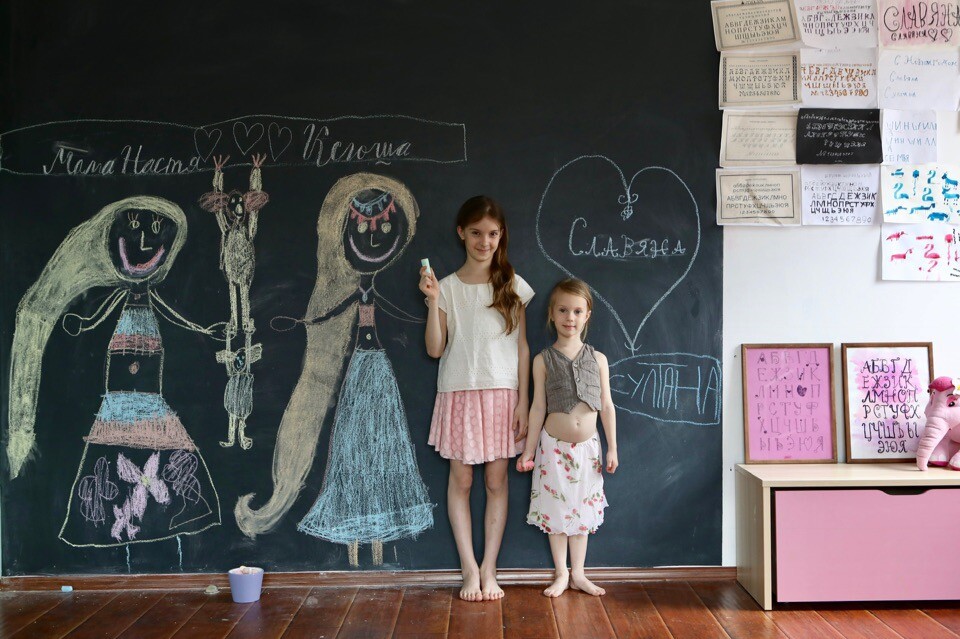
Когда я начала наши игры с буквами, встречала много сложностей на пути. Одна из них - примитивный взгляд на мир, отсутствие развитого творческого мышления. Дети не могли ничего сочинять. У них не было идей. Тоже самое я встречаю среди учеников курса.
После знакомства с разнообразием шрифтов они получают настоящее творческое задание. Создание собственного, уникального шрифта. Многие подходят к заданию креативно и выдают в результате интересные, необычные буквы! Фантазия бурлит и расшатывает даже “засохший мозг родителя”, они тоже начинают сочинять.
При этом есть дети, у которых это задание вызывает сложность. Нет креативных идей. И ребёнок не может выдать ничего, кроме стандартного написания прямых букв. И мамы в замешательстве…Как так? Где фантазия?
Если умение придумывать и сочинять не активировалось, не происходит запуска творческого мышления – значит есть какой-то зажим, запрет или страх у ребенка.
Хорошая новость - это исправимо в любом возрасте.
Так было у нас. Несмотря на то, что у нас художественная семья, когда я запустила игру с изобретением букв, у детей было только 1-2 идеи и все стандартные. Тогда я помогла им переступить привычную черту. Сделала вариант букв из пластилина, из блесток, из верёвок. И получила вопрос «А что так тоже можно?»
Стало очевидно, это моя вина, они начали мыслить шаблонами, не видят многообразие мира, как будто надели картонная коробку на голову и думают, что там внутри весь мир. А со временем эта коробка превратиться в железную и тогда будет сложно что-то менять.
И я стала менять... Понимаете, творческое мышление это не только про картинки, рисование и художников. Это про жизнь вообще, творческое мышление необходимо абсолютно в любой сфере нашей жизни! Это ВАЖНО! И раскрыть его можно разными способами. Один из них - “Игра в каллиграфию”
Спустя 4 года, у моих детей другое видение и наши занятия - это бесконечный и постоянный фонтан идей и задумок. Дети от природы выдумщики, для них нет границ и правил, они изучают и экспериментируют. НО, до определенного времени, пока правила не навешиваются со стороны и задача “нарисуй солнышко” превращается в “желтый круг и 6 палочек вокруг, а небо не бывает другого цвета, кроме голубого”.
Обычно такие трудности возникают у детей, которые уже познакомились с оценочной системой (хорошо/плохо, правильно/не правильно) и бояться совершить “неверный” шаг. Причина может быть в школе, или окружении родственников, когда кто-то в близком окружении твердит “не так надо, а вот так и вообще рисовать не умеешь”. В такие моменты пропадает вера в себя и желание поиска и развития творчества, фантазия блокируется, и ребенок пытается подстроиться под то, что он него требуют, ищет подходящий взрослым вариант, который оценят как “хорошо”. Становится обычным, без своих мыслей и идей. Пропадает уникальность и индивидуальность.
А ведь все в наших родительских руках. Помогите детям сохранить и развить креативность!
Мы по жизни создаём много напряжения, пытаемся ограничить детей во всех сферах, диктуем правила поведения в семье, в школе, ожидаем и требуем их исполнения, требуем дисциплины, и обычного копирования и повторения без выхода за пределы задания. Дети поддаются. И на выходе получаем то, что я описала ранее - ничего не может придумать. Нет идей.
- Осознать, что так есть и это надо исправить.
- Начать исправлять.
Здесь важно время. Подождите, дайте детям почувствовать свободу от шаблонов.
Есть такой термин «расшколивание» - у тех, кто переходит из школы на систему СО он значит, что ребёнку нужно дать время оправиться от той стрессовой ситуации, которая была в рамках ранее. Почувствовать свою силу выбирать, вернуться к ощущению свободы в образовании и творчестве.
Сколько на это уйдёт времени, никто не знает. У кого-то неделя, у кого-то больше, а кому-то нужен целый год. Зависит от степени травмы и зажатости.
У каждого ребёнка индивидуальный путь.
Давайте будем идти в спокойном режиме и наблюдать за детьми. Не ставьте никаких рамок, подождите, посмотрите. Дайте ему полную свободу в выборе материалов и способов выполнения задания, даже если вам кажется, что делает что-то не так - МОЛЧИТЕ. Наблюдайте.
Знаете, от учеников курса у нас уже целая коллекция изобретений.
Посмотрите, настолько активно включается творческое воображение. И в лесу буквы, и буквы-овечки и облачка. А еще в предыдущем потоке у нас был папа-изобретатель.
Сегодня расскажу вам историю про папу, который участвует вместе с детьми и придумывает необычные решения для заданий курса. Одно из них мне очень понравилось. Такого варианта еще не было. Дети делали буквы из разных материалов. Наклеили и сделали объемную букву В из бумаги (можно из проволоки попробовать). Когда просто смотришь на лист, буквы не видно, но направить свет со стороны, то он падая на бумагу, создает тень и В появляется.
Круто)))
Это папа. Это мужской взгляд, чистое изобретательство.
Если вам интересно - попробуйте этот вариант с детьми.
Подробности в карусели.
Всегда радуют папы! Спасибо им за идеи и прекрасную практику. Веселую и интересную. Она совсем не про письмо и красивый почерк...она про любовь и смысл к самому процессу, креативность и умение строить свою жизнь, как конструктор лего.
Я люблю подход “Есть задача - найди решение”. Он здорово помогает научиться решать проблемы и справляться с трудностями!
А они возникают повсеместно, от простого “сделал, а у меня получилось плохо или не получилось” до глобального “жизнь такая сложная”
Знакомо? А как часто вы сталкиваетесь с проблемой “не получается” у детей?
Научите детей находить решения в любой ситуации.
Это очень важный навык в жизни! Покажите своим примером, что адаптировать под обстоятельства можно любую ситуацию!
Изменять и совершенствовать любую задачу МОЖНО и НУЖНО!